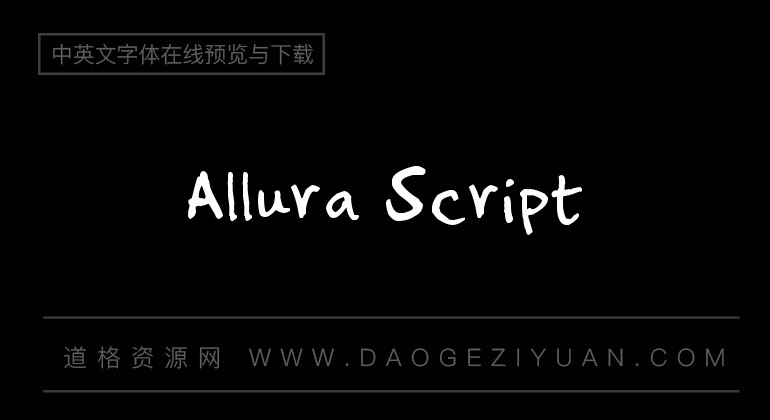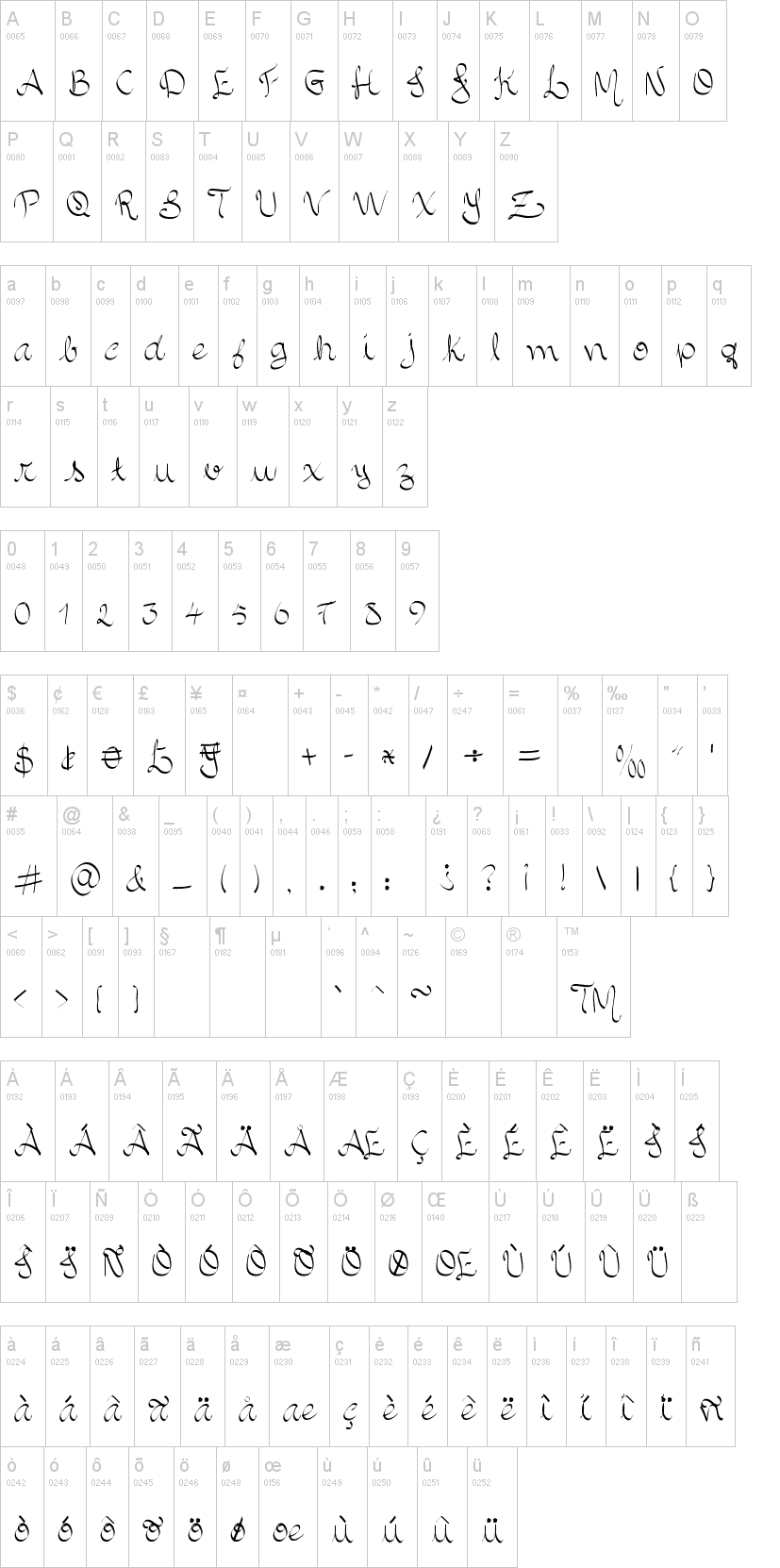
Allura Script
Allura Script是一款免费的手写风格字体,由设计师Roberto Mocci创建。该字体适用于各种用途,如品牌设计、海报、标志、广告和电子邮件。 Allura Script的特点是优美、流畅的笔画和连字。它的形状和曲线使文本看起来像手写,具有一定的个性和温暖感。此外,该字体在多种大小和分辨率下良好地呈现。 Allura Script支持多种语言和字符,包括西班牙语、法语、德语、意大利语、葡萄牙语、荷兰语、土耳其语和斯堪的纳维亚语。它是一种非常通用的字体,适合多种品牌和设计项目。 总之,Allura Script是一种优美、流畅的手写风格字体,适用于各种品牌设计和广告项目,是一种非常实用的字体。
Allura Script是一款非常不错的手写艺术字体,具有很好的视觉感,适合于文化类的宣传设计、商业类品牌的广告和产品包装设计以及个性化文字排版等较多场景。
Allura Script字符映射图